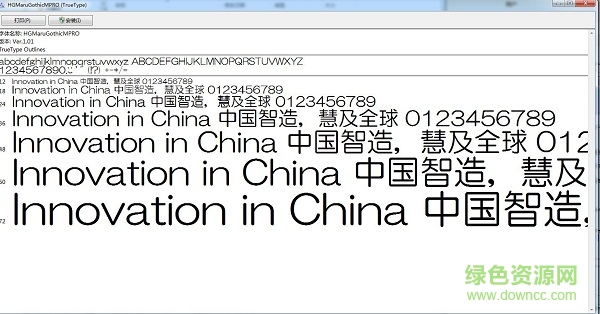
hgmarugothicmpro
hgmarugothicmpro字體是一款常見的日文字體,支持基本拉丁文、中日韓符號(hào)和標(biāo)點(diǎn)的輸入,字型端正規(guī)范,號(hào)召力強(qiáng),適用范圍廣泛,需要的朋友快來本站免費(fèi)下載吧!
hgmarugothicmpro